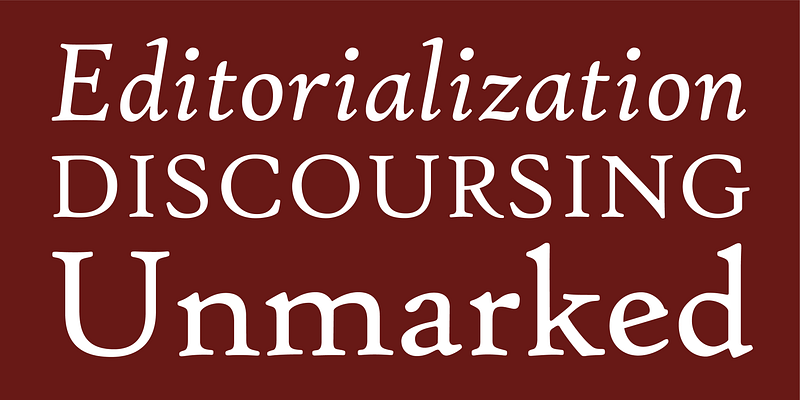
Hightower es una versión suave y entintada del género de tipografías “veneciano”, que surgió con la letra romana de Nicholas Jenson de 1470. Las proporciones amplias y los colores intensos de Hightower se calibraron para textos pequeños. Sus formas y detalles orgánicos también funcionan bien en titulares, donde aportan complejidad y sutileza.